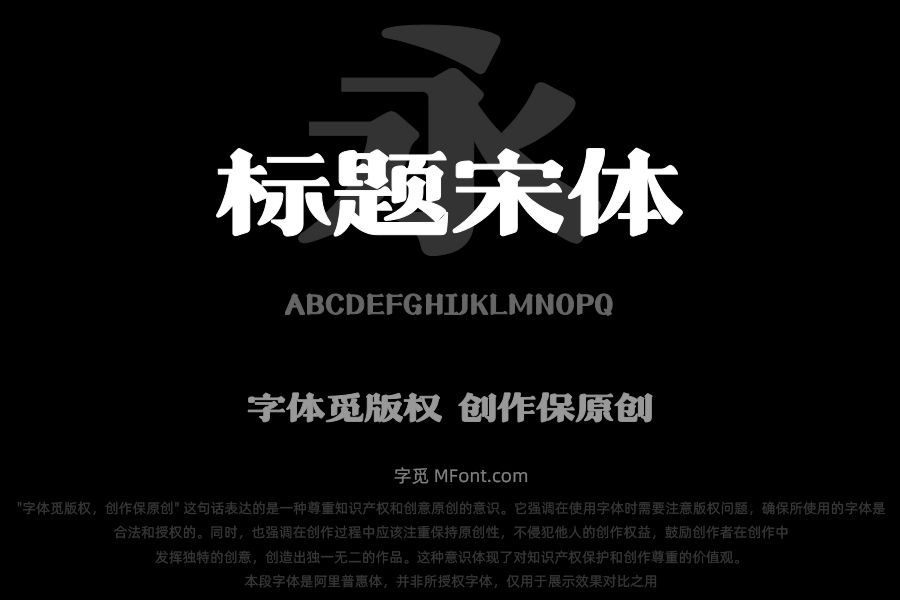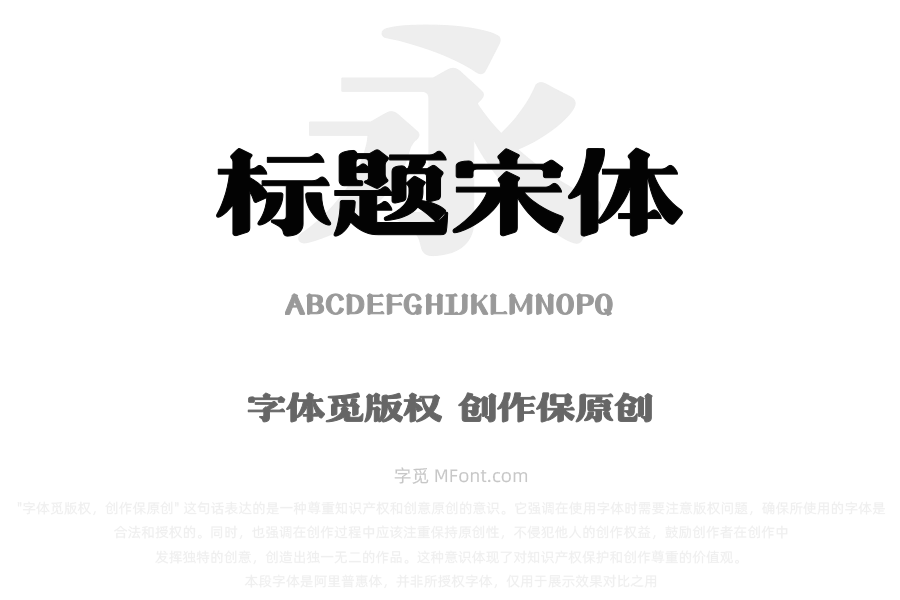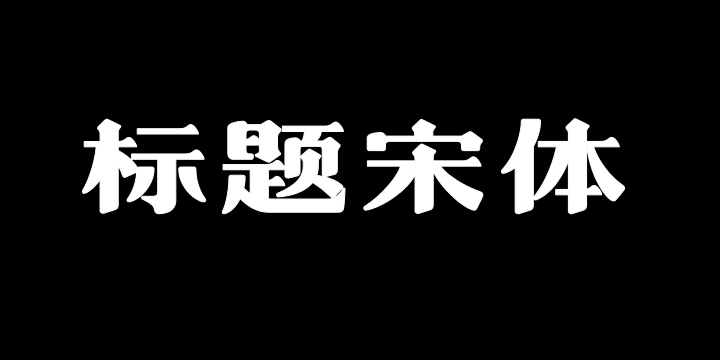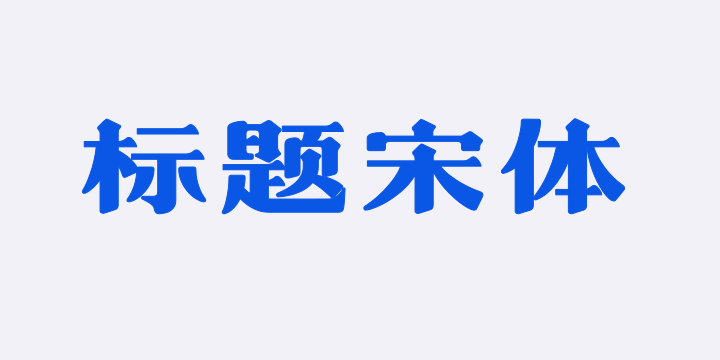
字体全名: 上首标题宋体
字体简介: 上首标题宋体,简体中文约6763字,在保留传统宋体“横细竖粗、饰角明显”的结构基因基础上,进行了重创造性突破。横竖笔划增加了突出的尖角、具有轻奢、文艺。字体风格稳重呈方块形,整体特征坚硬、有力。具有现代、国际化的指向性字形紧凑,但不失美感。刚正而不失稳重,横竖笔画加人了尖突的效果,让字形更显英朗气质。突出个性,端庄秀美。